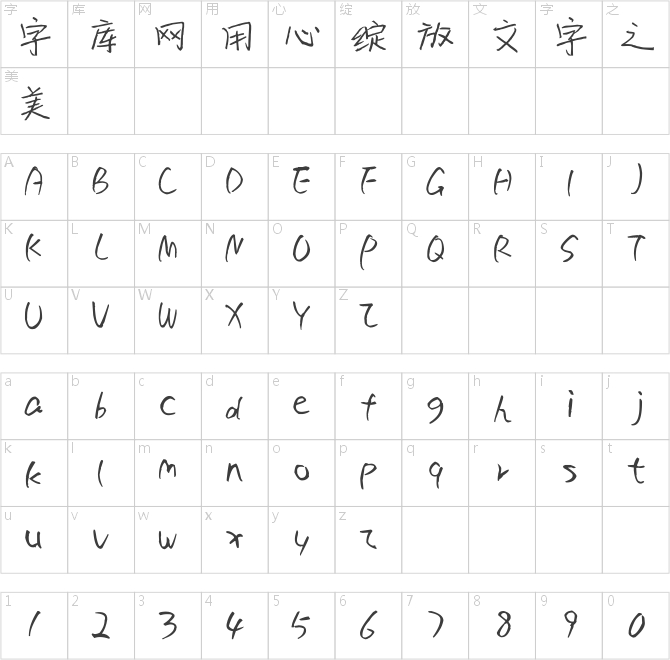
蟬羽安好晴天 詳情頁
字體名稱: 蟬羽安好晴天
蟬羽安好晴天
蟬羽安好晴天介紹
蟬羽安好晴天字體字庫是一款讓人賞心悅目、百看不厭的中文字體,適合各類廣告和產(chǎn)品包裝設計應用,字體大小6.06MB,格式為ttf字體,上傳用戶是志誠設計,作者/版權(quán)方為蟬羽字庫
蟬羽安好晴天效果圖